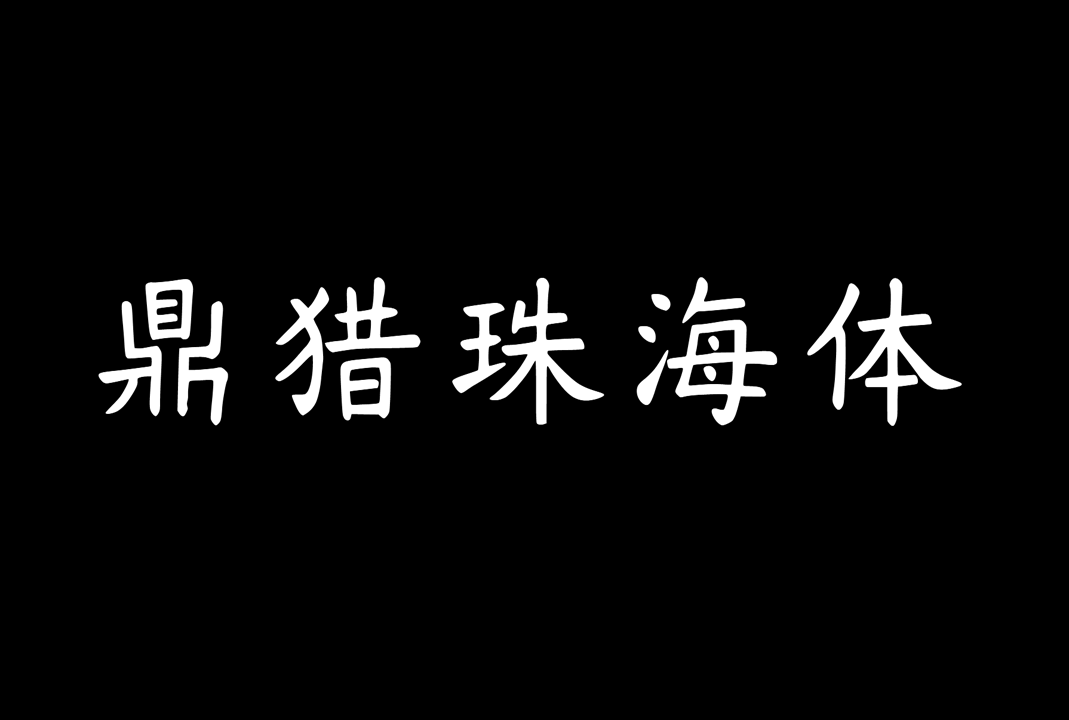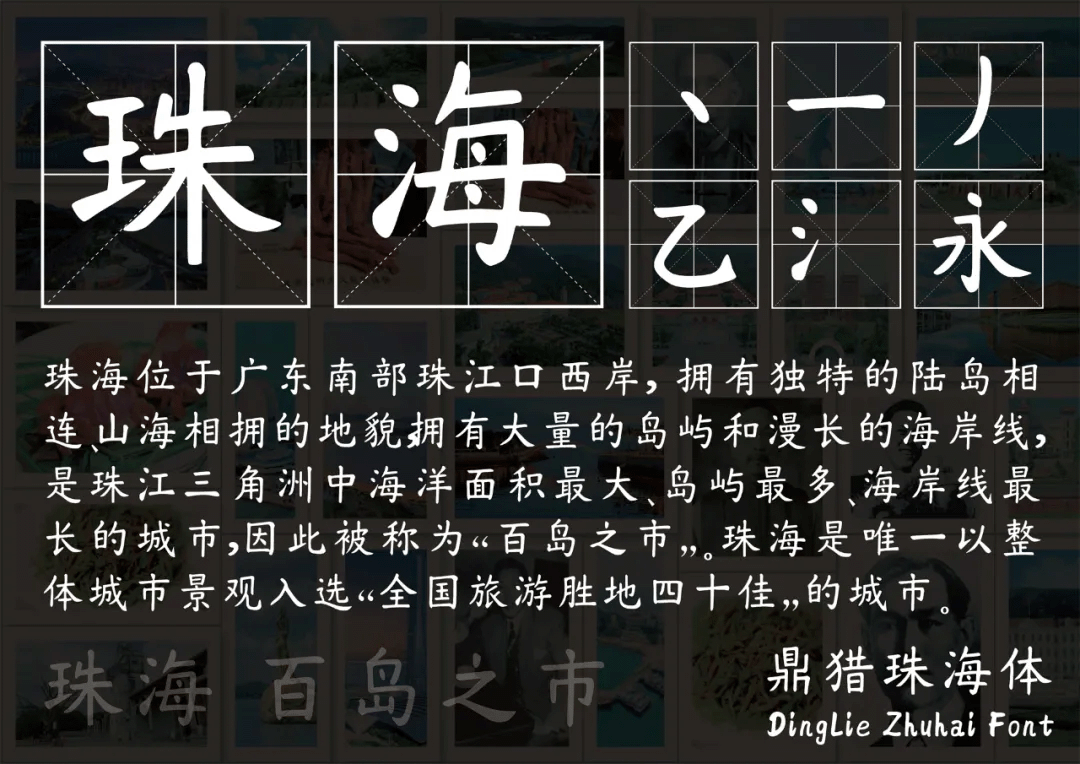
鼎猎珠海体(dingliezhuhaifon)为一款原创字体,是由鼎猎咨询于微信公众号发布声明的一款中文免费商用字库,具有其独特的字形风格,适用于广告、书籍、海报等多个场合。
鼎猎客家体(dingliezhuhaifon)根据简体中文汉字编码国家标准(GB2312编码)设计,共计设计了多达7905个字符,其中汉字6916个。在6763个汉字基础上,特别增加了153个常用粤语汉字,可覆盖大部分使用场景。